Een grote in het lettervak vind ik hem. Brody Neuenschwander, kalligraaf, een Amerikaan anno 1958,
nu wonend en werkend in Brugge en perfect Nederlands sprekend. Zijn kalligrafisch
werk strekt zich uit tot ver buiten de gebaande wegen. Zo werkte hij mee aan de films
Prospero’s Books en Pillow Books van Peter Greenaway, waarin Brody live teksten
schreef op de lichamen van acteurs. Maar ook schreef hij bijvoorbeeld teksten die live en gigantisch groot werden geprojecteerd op een toren in Bologna. Hij is een onderzoeker, hij experimenteert, is actief in binnen- en buitenland, geeft cursussen, exposeert. En hij bestudeert de Arabische,
Chinese en Japanse kalligrafie, wat weer zijn eigen werk beïnvloedt: samensmeltingen
ook dát allemaal mogelijk is met letters. Nee, kalligrafie is zo suf nog niet!
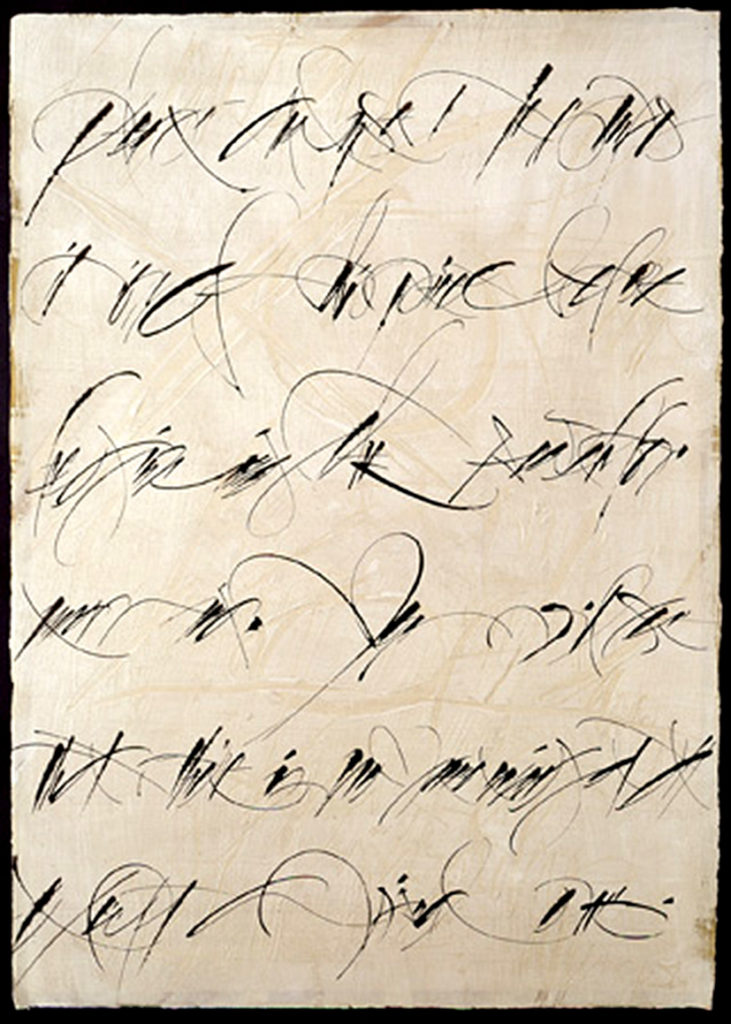
Brody is een uitzonderlijke kunstenaar.
Lang geleden zag ik hem aan het werk in museum Meermanno; zoals hij de pen
op papier zet; alsof hij in zijn hoofd de lijnen al klaar heeft liggen.
Ook zijn teksten bij het grote “Rijks” boek zijn verbijsterend mooi.